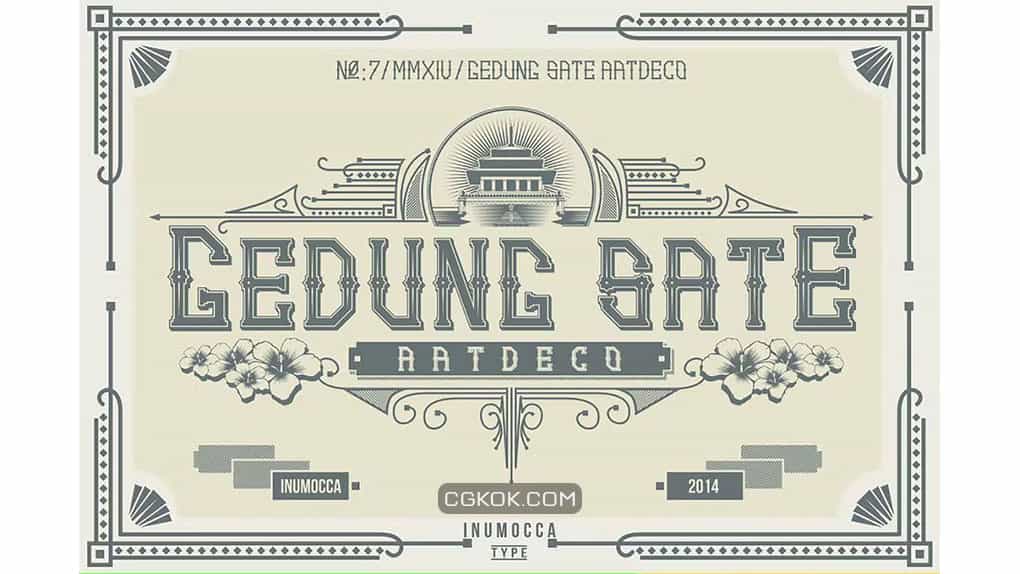
فونت انگلیسی GS.ArtDeco Family Font : این فونت با الهام از تزئینات، ساختمان و سبک معماری ساختمان Gedung sate واقع در باندونگ، اندونزی طراحی شده است. این فونت برای گروه، شرکت، برچسب، کمپانی پوشاک، محتوای کلاسیک و … مناسب می باشد.
• سبک: Serif
• فضا بین حروف: معمولی
• اندازه بهینه: بزرگ (نمایش / پوستر)